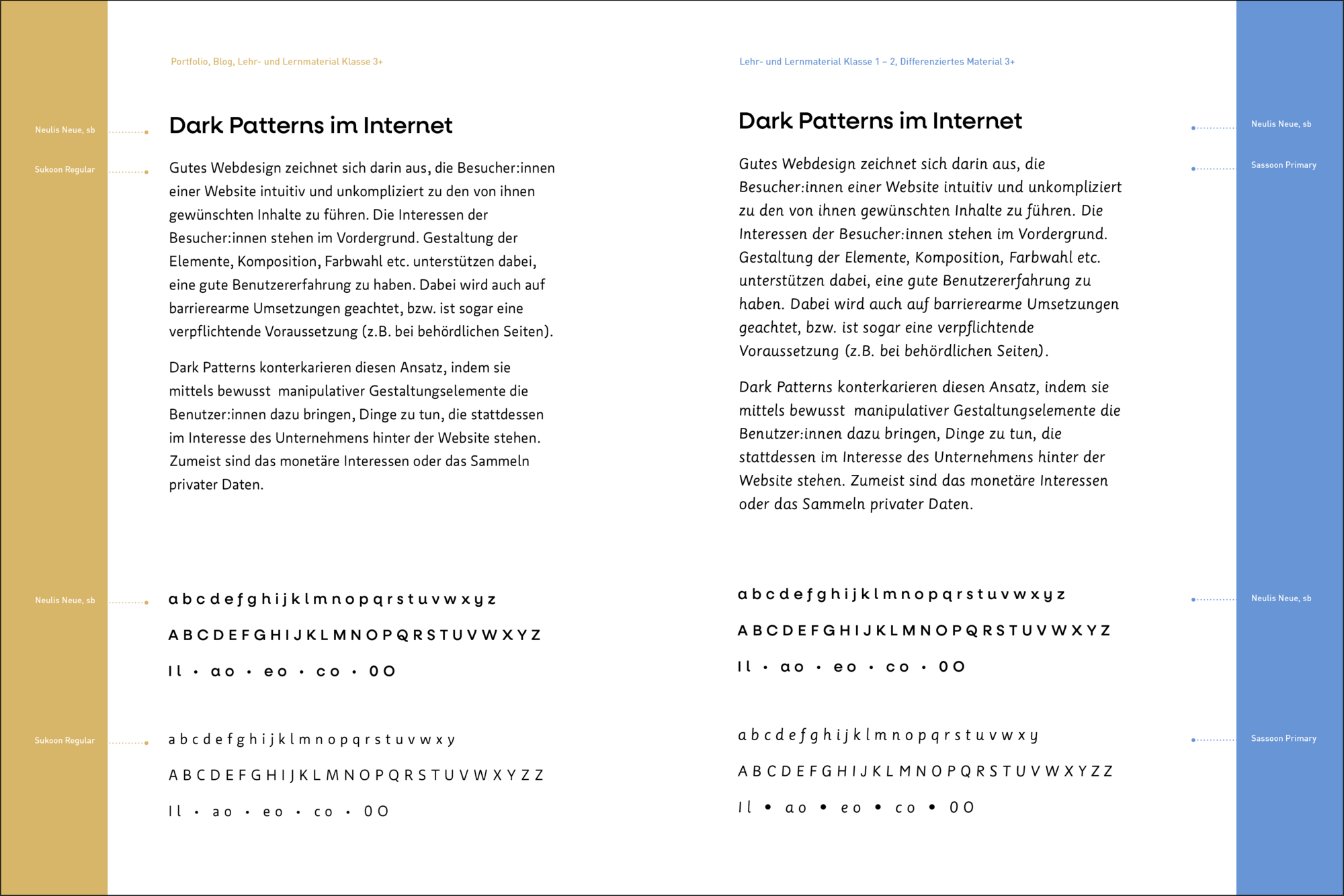
Schriftkombination für Online und Print - Fokus Lernmaterial
ich bin auch einmal wieder auf der Suche nach einem schönen Schriftpärchen (Display/Text).
Zum Einsatzzweck
Die Schriften sollen in verschiedenen Kontexten verwendet werden:
• Auf meiner Portfolio-Website (digital) für Infoseiten (LXD- und UX-Design)
• In einem auf der Website betriebenen Blog (Medienkompetenz, Digitales Lehren und Lernen, LXD)
• Für Lehr- und Lernmaterial (Print und Digital), das primär in den Klassenstufen 1 – 6, mehr 4 – 6 eingesetzt wird
• Auf Printprodukten im eigenen Corporate Design (Visitenkarte, Briefbogen) - allerdings nur sehr wenig
Zielgruppen
• Erwachsene: Lehrer und Lehrerinnen, in kleinem Umfang Auftraggeber im Bereich LXD- und UX-Design
• Schüler und Schülerinnen (Bearbeitung des Materials), primär im Alter von 8 – 12.
Überlegungen
Die Website werde ich für Portfolio-Aspekte und den Blog unter meinem Namen betreiben. Für das Lernmaterial das ich anbiete arbeite ich mit einem eingängigeren fiktiven Markenbegriff als Unterbereich auf der Website. Diese Marke werde ich dann auch über Social Media bewerben. Das grob zum Hintergrund.
Ich hatte überlegt ob ich zwei verschiedene Schriftpaare nehme: Eine für Portfolio/ Dienstleistungen und ein zweites für das Lernmaterial. Allerdings bevorzuge ich einen klaren visuellen Zusammenhang. Ich will das Lernmaterial auch lieber seriöser halten mit einer gut lesbaren Schrift und es dann anderweitig kindergerecht gestalten.
Eine Variante wäre es, für die Headlines zwei Schriftarten zu suchen, eine für die Website/Corporate und eine für die Überschriften des Lehr- und Lernmaterials, wenn es sich an die jüngeren Kinder richtet. Font für den Fliesstext würde ich in beiden Fällen aber identisch lassen.
Oder eben am Ende doch zwei getrennte Schriftkombinationen. Nur wie erwähnt: Zu verspielt sollte es bei den Lernumgebungen nicht werden. Da bin ich noch hin und hergerissen und offen für eure Sichtweisen.
Anforderungen an die Schriften
• Gut lesbar sowohl in Print und Digital
• Keine Präferenz hinsichtlich Serifen/Semi-Serif/Serifenlos
• Breite Auswahl an Schriftschnitten
• Gute Unterscheidbarkeit kritischer Buchstabenpaare:
• I und l (großes I und kleines l)
• e, c, a / o
• Zahl 0 und Buchstabe o
• Ich bin Freund davon, wenn die Schriften kleine verspielte Details haben, ohne auf Kosten der Lesbarkeit (Beispiel Neulis Alt)
• Theoretisch wäre Adobe Fonts vorhanden, würde aber am Ende ohnehin lizensieren um den/die Typografin stärker zu unterstützen
• Google Fonts muss nicht sein
Bisherige Überlegungen
Folgende Pärchen hatte ich einmal überlegt, aber ist nur ein loser Anfang und Typografie ist nicht mein Steckenpferd.
• Marat (Text) und Aspen (Display) *
• GT Maru (Text) und GT Planar (Display)
• TT Norms Pro Serif (Text) und TT Norms Pro (Display)
Über Vorschläge bin ich sehr dankbar. Gerne auch was mit etwas Pep, "geheime/neue" Fonts die nicht so "abgelutscht" sind wie z.B. die Norms.
Kleine Präzisierung.
Ich habe selber noch ein wenig weiter gesucht und probiert und bin bei der Sukoon hängen geblieben, die für den Fliesstext meine Kriterien an die Buchstaben gut erfüllen würde. Ich bin nur nicht ganz sicher, ob sie mir nicht eine Spur zu weit läuft. Sie ist aber ein heißer Kandidat. :)
Für die Headlines habe ich einmal drei Kombinationen ausprobiert:
• Neulis Neue: Die Neulis hat die besten Buchstabenunterscheidung und wirkt dezent verspielter, was hinsichtlich Zielgruppe Kinder ein Plus ist, aber irgendwas fühlt sich bei der Kombination nicht ganz richtig an.
• Aspen: Die Aspen gefällt mir auf Anhieb gut in Kombination, ist aber eher konservativ.
• Hypatia Sans Pro: Auch eine Variante. :)
Was meint ihr. Richtige Richtung?
Ggf. Neulis/Sukoon für das Lehr/Lernmaterial und Aspen/Sukoon für Portfolio/Website/Blog?
Lizenzen für Aspen und Neulis habe ich bereits, müsste also theoretisch nur noch die Sukoon erwerben.
Je mehr ich mit den Schriften probiere desto mehr komme ich nun doch zu stärker differenzierten Schriften beim Fliesstext:
Fliesstext
• Sukoon: Portfolio, Lehr- und Lernmaterial ab 3. Klasse
• Sassoon Primary: 1. – 2. Klasse und differenziertes Material ältere Schüler
Headlines
• Neulis: Konsequent für alle Überschriften. Passt dann besser zur Sassoon und hat dann doch ein auffälligeres verbindendes Element im Vergleich zur Aspen - auch wenn ich letztere immer noch eine Spur harmonischer finde)
Die Sukoon erscheint mir schwierig lesbar. Für Überschriften wird sie gut funktionieren, für Fließtext würde ich sie aber nicht verwenden. Wenn du Serifenlose suchst, würde ich mal »Atkinson Hyperlegible«, »Andika« oder »Source Sans 3« anschauen.
Würdest Du die Sukoon grundsätzlich nicht für Fließtext verwenden? Ich meine die von Fontwerk. es gibt ja auch noch andere. Bei Leseanfängern gehe ich da klar mit, daher auch der Gedanke zur Differenzierung in unteren Stufen. Ansonten empfinde ich sie schon als gut lesbar. Aber das soll ja am Ende keine Einzelmeinung sein.
Im Anhang einmal die Gegenüberstellung meiner aktuellen Überlegung. WIP.